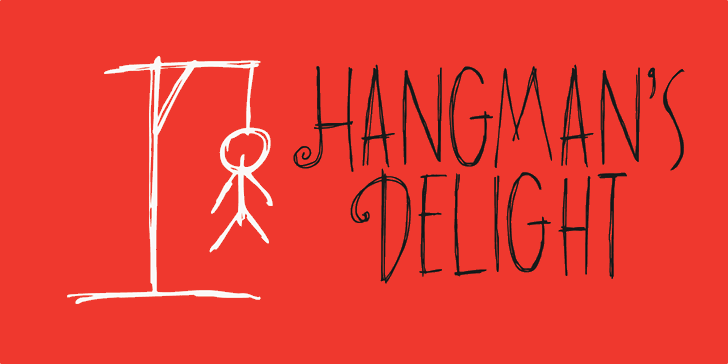
A fonte ‘DK Hangmans Delight Font’ é uma herança do estilo das escritas manuscritas, criada pelo designer Hamilton. Inspirada nas curvilíneas leves e delicadas de letras ao vivo, esta fonte oferece um toque romântico perfeito para criações de design pessoais ou até mesmo para trabalhos que visam uma atmosfera mais aconchegante. Ideal para gráficos sem fins comerciais, o uso deste tipo de letra é livre e não deve ser copiado para aplicações como jogos, aplicativos ou programas. Se você está planejando usar esta fonte de forma comercial ou em produções que possam ser distribuídas, recomendamos obter uma licença oficial. Você pode encontrá-la na nossa página onde também encontrará todos os extras e recursos associados: www.hanodedfonts.com. Não se esqueça de consultar o arquivo FAQ para todas as informações relevantes.